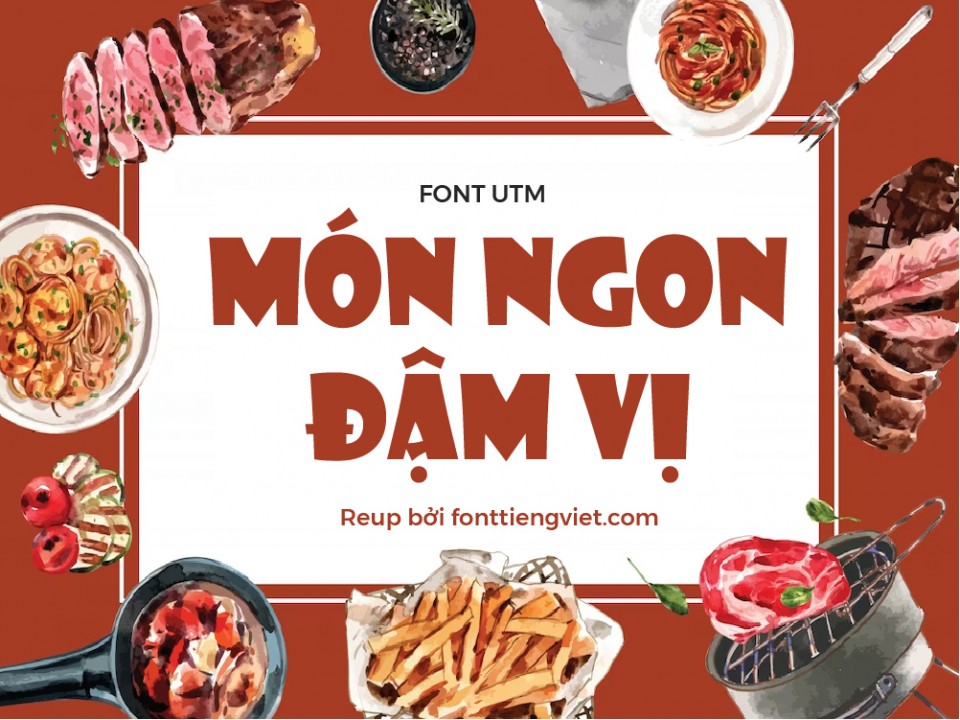
Font việt hóa UTM Showcard
Giới thiệu về Font việt hóa UTM Showcard
Trong thế giới đồ họa, việc lựa chọn một Font Miễn Phí phù hợp là yếu tố then chốt để tạo nên sự ấn tượng cho tác phẩm. Font việt hóa UTM Showcard là một trong những bộ phông chữ nổi bật nhất thuộc hệ thống UTM, được tinh chỉnh hoàn hảo để phù hợp với bảng mã Unicode tiếng Việt. Với phong cách thiết kế dày dặn, mạnh mẽ và đầy cá tính, bộ chữ này mô phỏng lại các nét vẽ tay trên biển quảng cáo cổ điển, mang đến cảm giác gần gũi nhưng không kém phần chuyên nghiệp cho người xem.
Đặc điểm nổi bật của font chữ
Đặc trưng lớn nhất của Font việt hóa UTM Showcard chính là các đường nét bo tròn mềm mại kết hợp với độ đậm (bold) cực kỳ cao. Điều này giúp văn bản luôn nổi bật dù đặt trên những nền hình ảnh phức tạp. Các bạn học sinh có thể sử dụng font này để làm tiêu đề bài thuyết trình, trong khi nhà trường có thể ứng dụng vào các băng rôn sự kiện. Sự kết hợp giữa nét cổ điển và hiện đại giúp bộ font không bao giờ lỗi mốt trong các dự án sáng tạo nội dung số.
Cách ứng dụng Font việt hóa UTM Showcard hiệu quả
Để phát huy tối đa vẻ đẹp của Font việt hóa UTM Showcard, bạn nên sử dụng chúng cho các tiêu đề chính hoặc các cụm từ ngắn cần tạo điểm nhấn. Do đặc tính nét chữ dày, bạn không nên dùng font này cho các đoạn văn bản dài vì sẽ gây cảm giác nặng nề, khó đọc. Thay vào đó, hãy phối hợp nó với các font chữ không chân thanh mảnh để tạo ra sự cân bằng thị giác. Việc áp dụng màu sắc rực rỡ hoặc hiệu ứng đổ bóng cũng sẽ làm tăng thêm sức sống cho bản thiết kế của bạn.
Kết luận và tải xuống